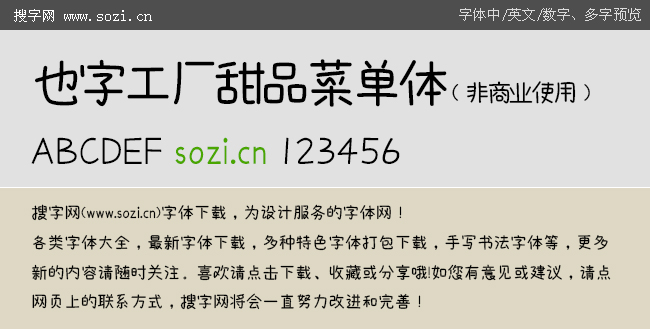
也字工廠甜品菜單體
搜字網(wǎng)給大家提供一款也字工廠甜品菜單體(非商業(yè)使用)中文字體下載,也字工廠甜品菜單體是一款略帶卡通風(fēng)格的手寫(xiě)字體,字體書(shū)寫(xiě)天真可愛(ài),充滿童趣。適合應(yīng)用于兒童繪本、兒童海報(bào)、網(wǎng)頁(yè)設(shè)計(jì)等應(yīng)用(此字體為個(gè)人非商用版,商用可以聯(lián)系:官方網(wǎng)址:https://yefont.com/home,聯(lián)系方式:13798980448)。